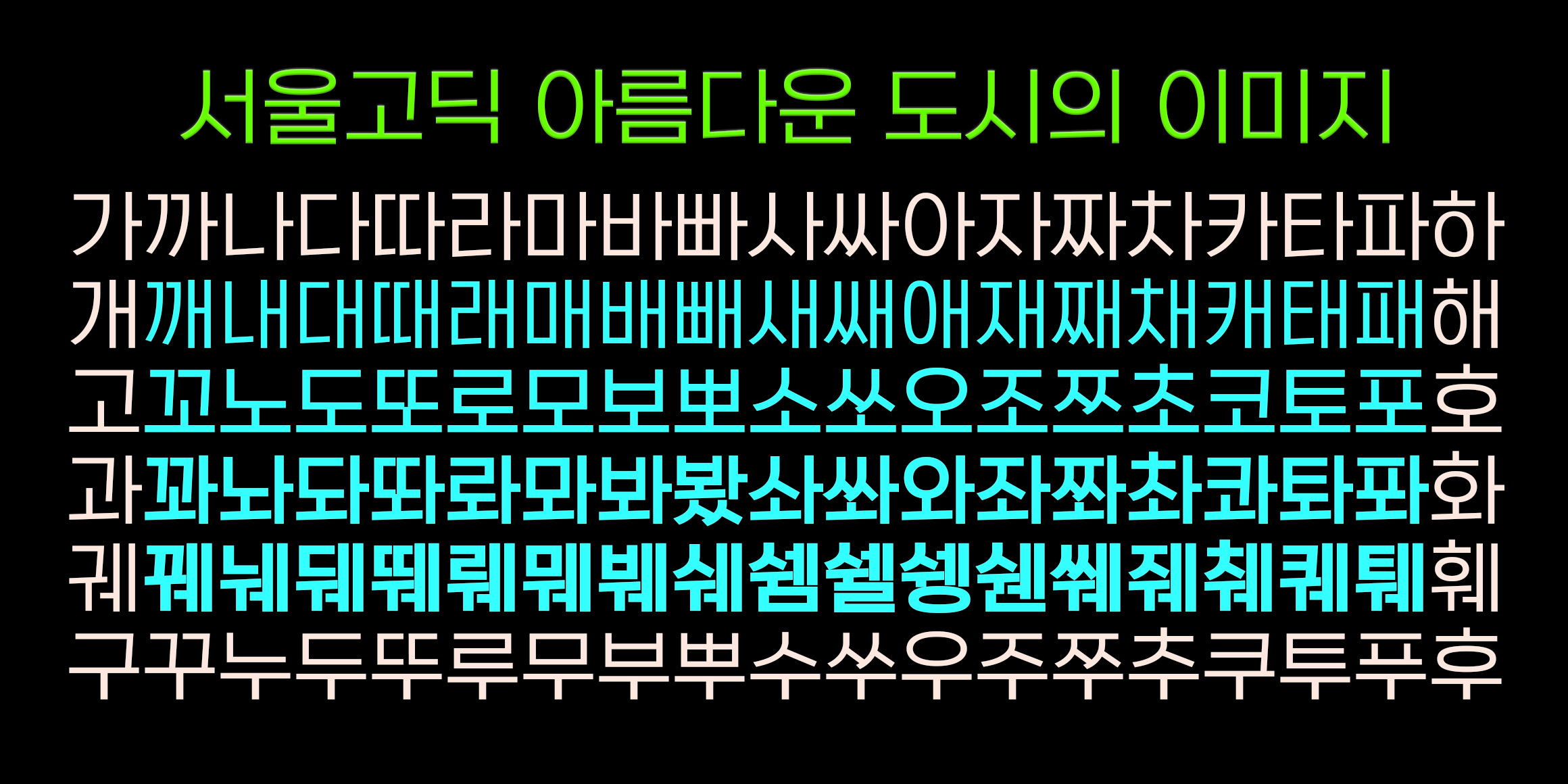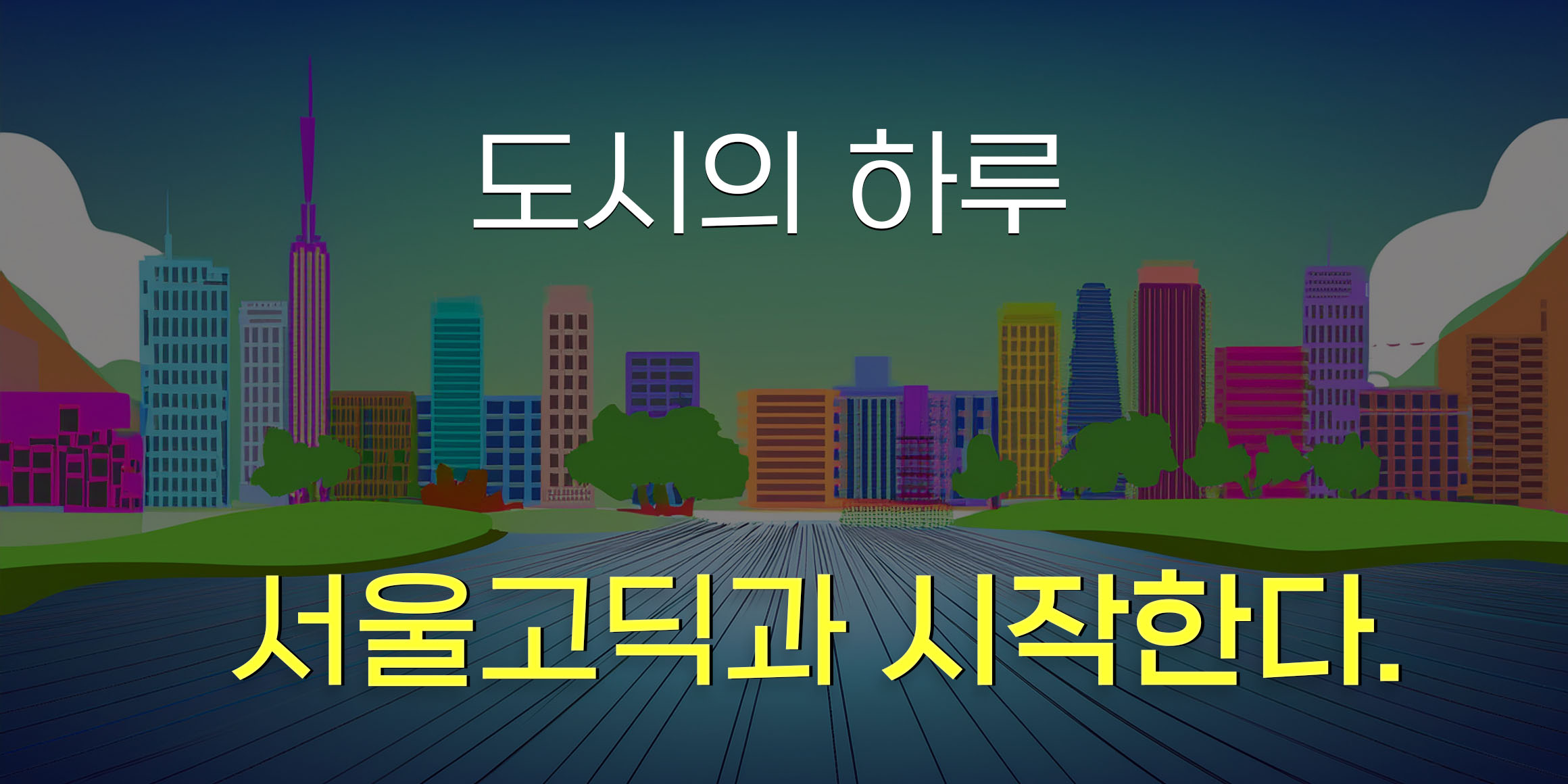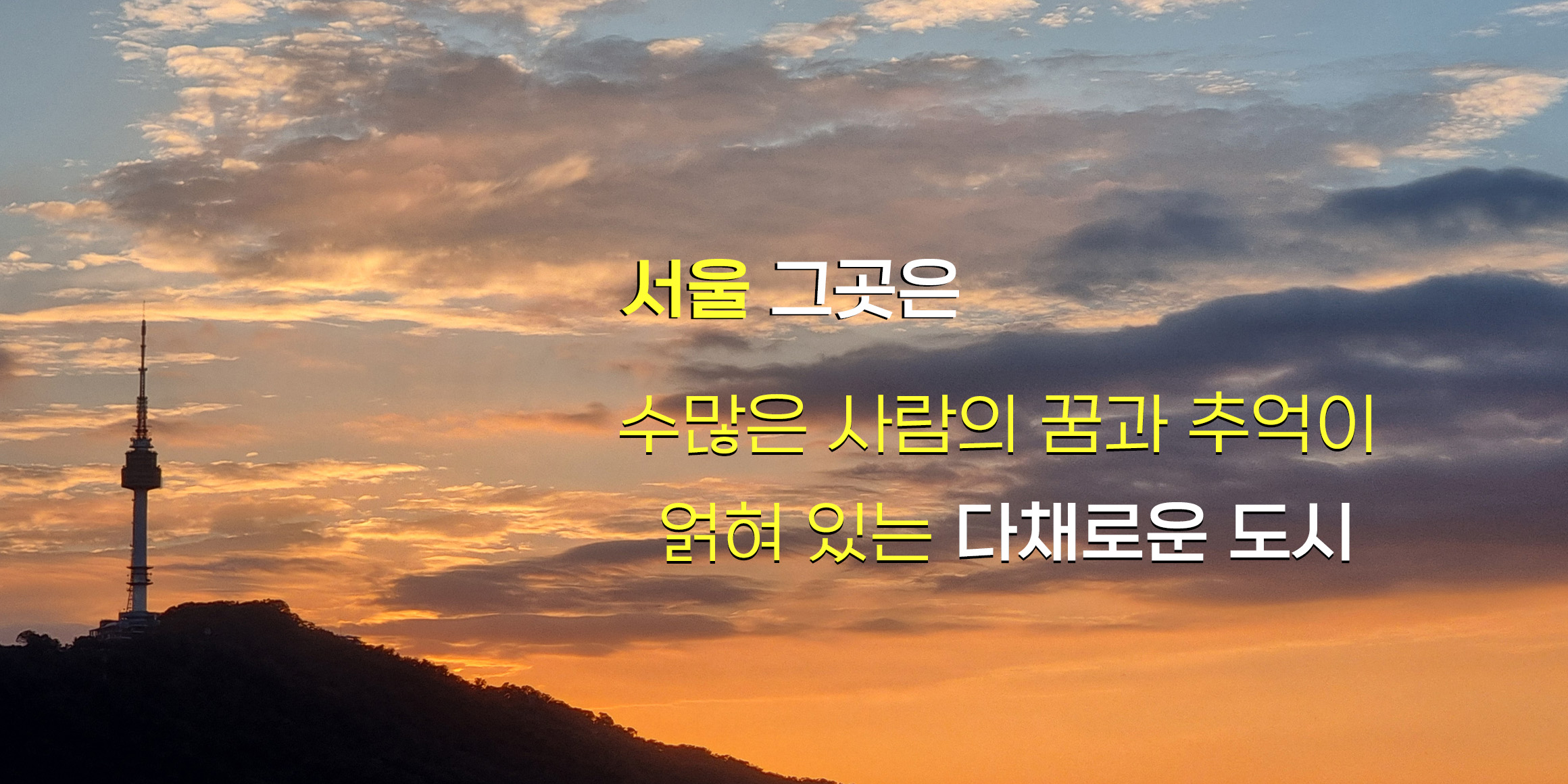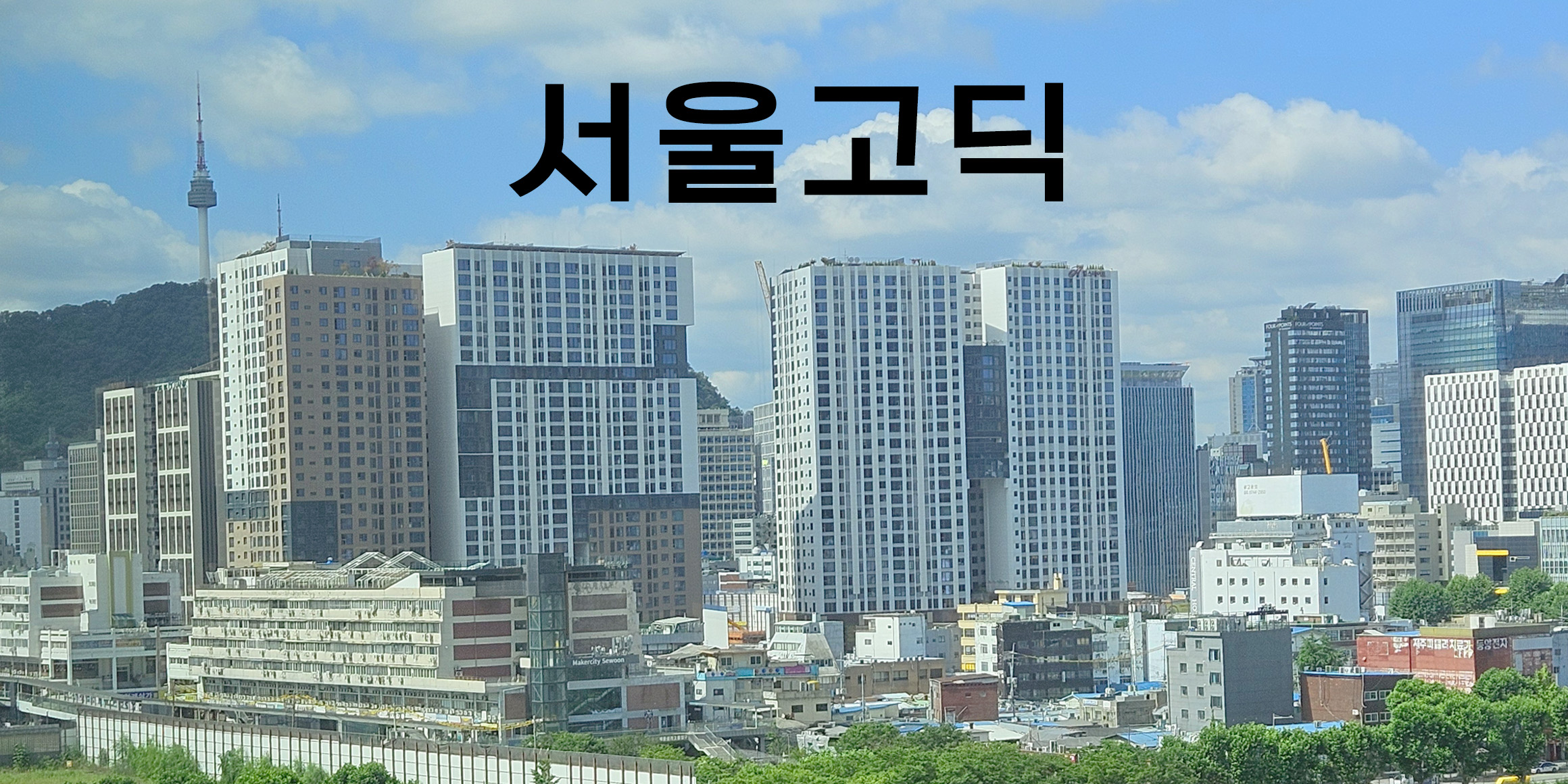
DX서울고딕
분류 Sans,디스플레이,민부리
제목용본문용현대적
빠르게 변화하는 대도시 서울의 에너지와 안정적인 균형을 담아낸 서체입니다.
사각 프레임을 가득 채우는 탄탄한 구조와 밀도를 표현하고, 균형 잡힌 획과 안정적인 비례는 뛰어난 가독성을 제공합니다.
특히 ㅅ, ㅈ, ㅊ 계열의 내리획의 경우 곡선과 직선을 교차 적용하여 기존 고딕체와 차별화된 개성을 부여하여 서울이 가진 역동성과 인간적인 감성을 동시에 상징합니다.